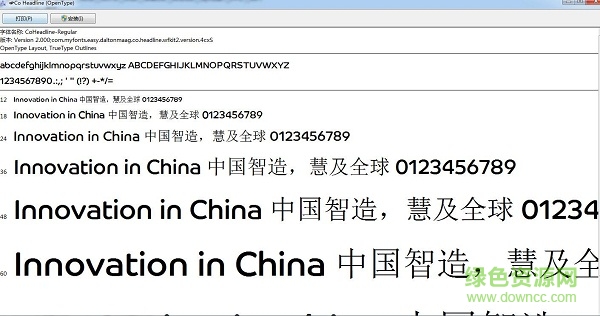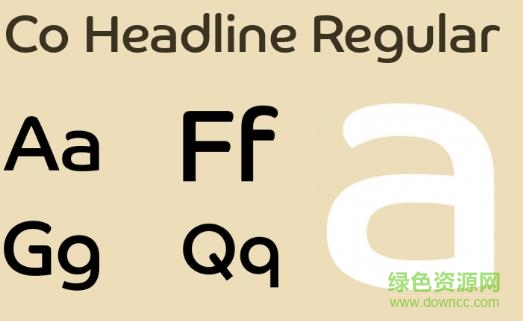
coheadline regular
coheadline regular字體是一款優(yōu)雅的英文字體,筆形柔和,結(jié)構(gòu)輕巧,粗細(xì)結(jié)合得當(dāng),十分地好看,適合用在平面設(shè)計(jì)等領(lǐng)域,歡迎大家免費(fèi)下載!
coheadline regular
無襯線字體特征
該類字體通常是機(jī)械的和統(tǒng)一線條的,它們往往擁有相同的曲率,筆直的線條,銳利的轉(zhuǎn)角。